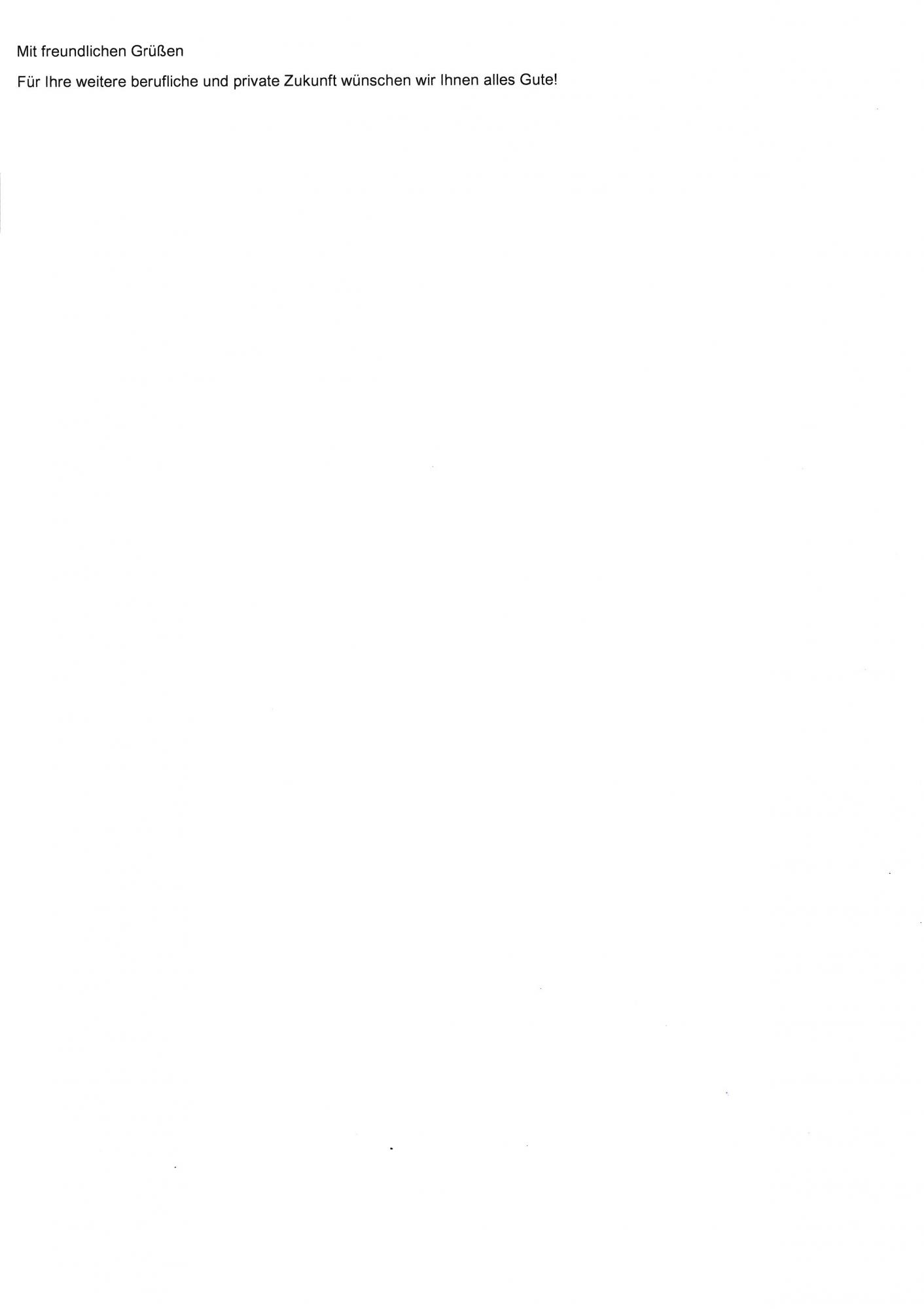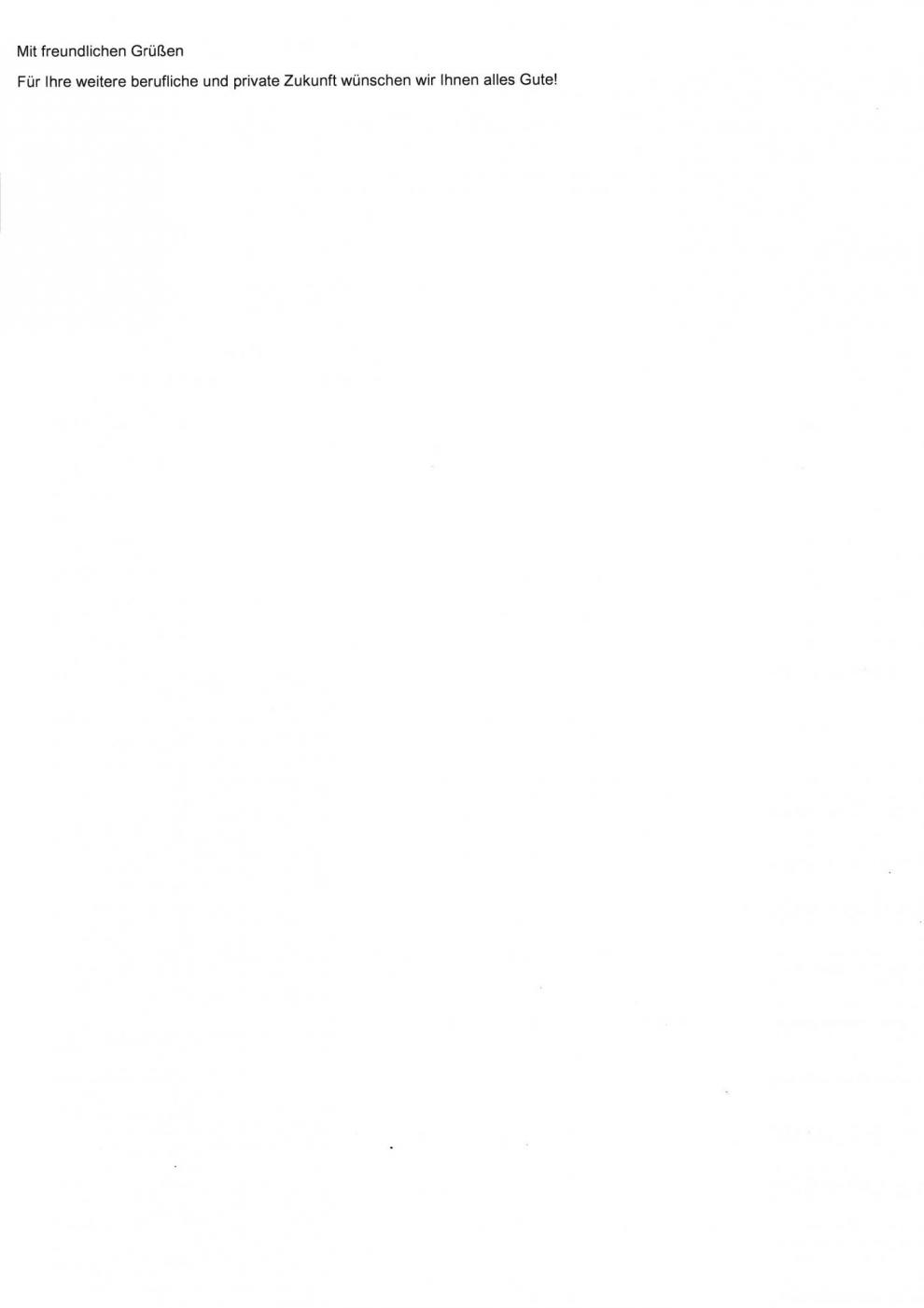
Mitarbeiter schreiben , ist die schrift in Ordnung
Würde gern die Schrift für ein schreiben benutzen, um ein Dankschreiben zu verfassen.
ist die Schrift ok, oder sollte ich eine andere Wählen?
Um welche handelt es sich bei dem Beispiel ?
Das ist die Arial, Systemschrift von Windows. Spricht nichts dagegen, sie zu verwenden, außer euer Corporate Design schreibt eine andere Schriftart vor.